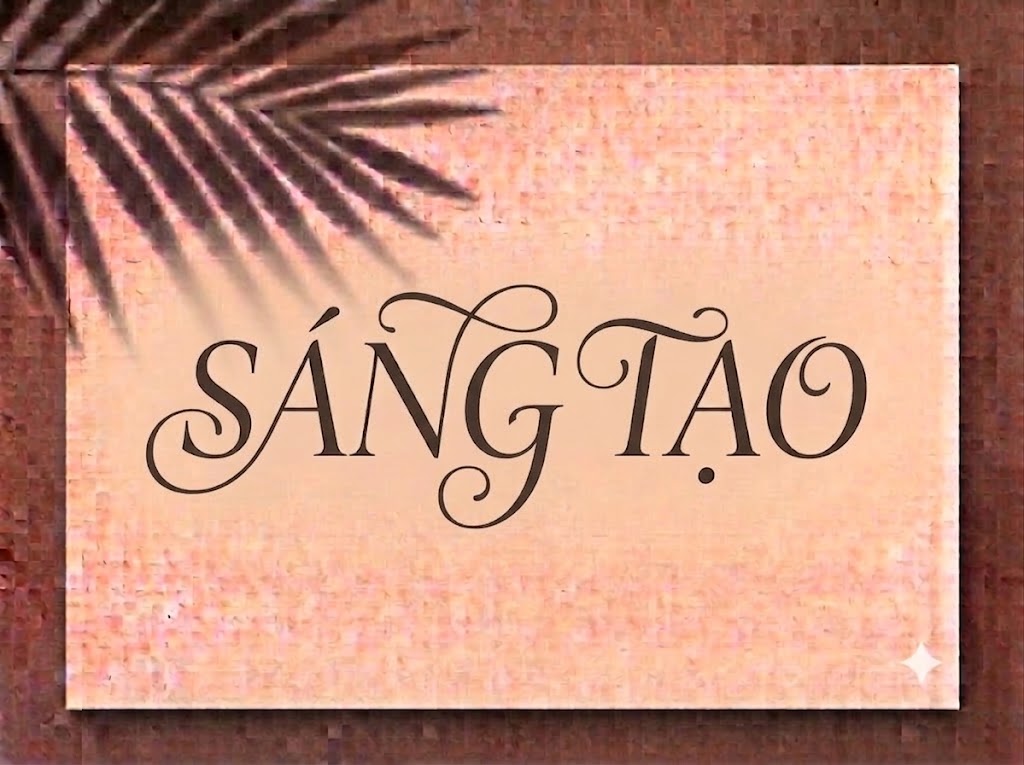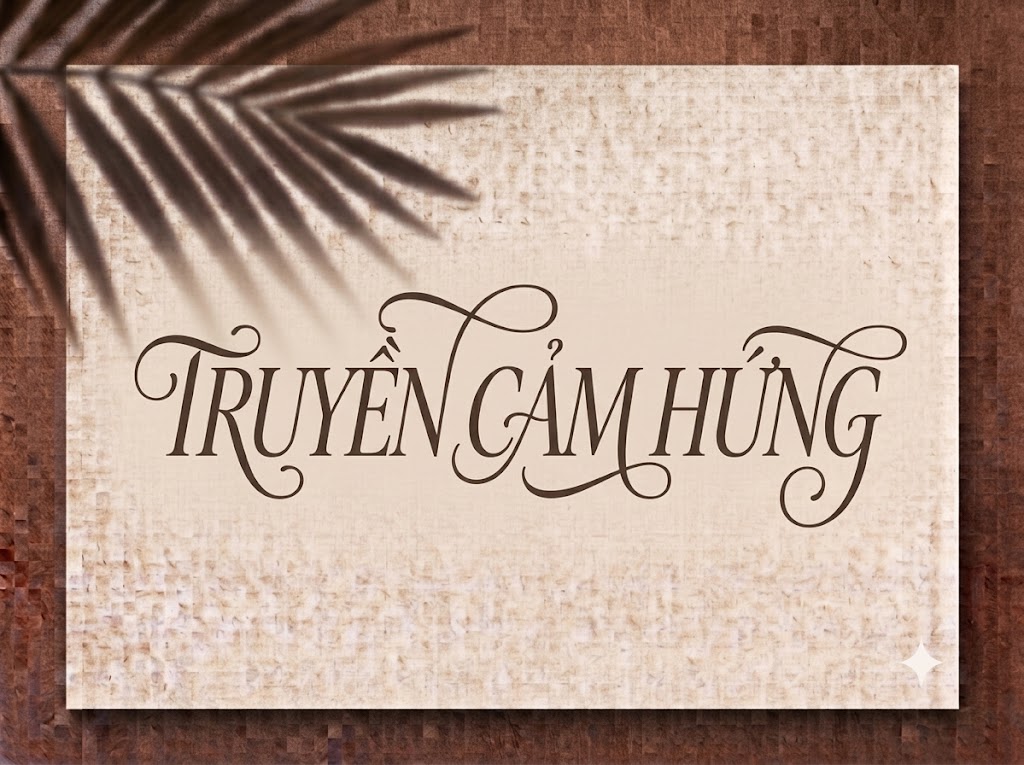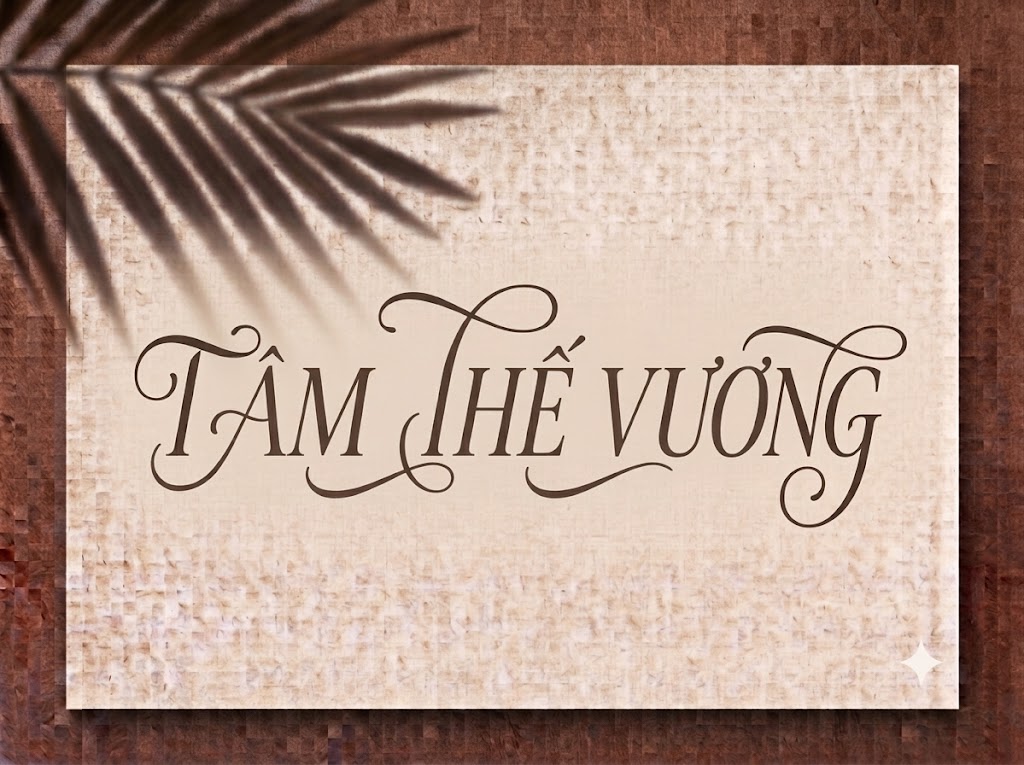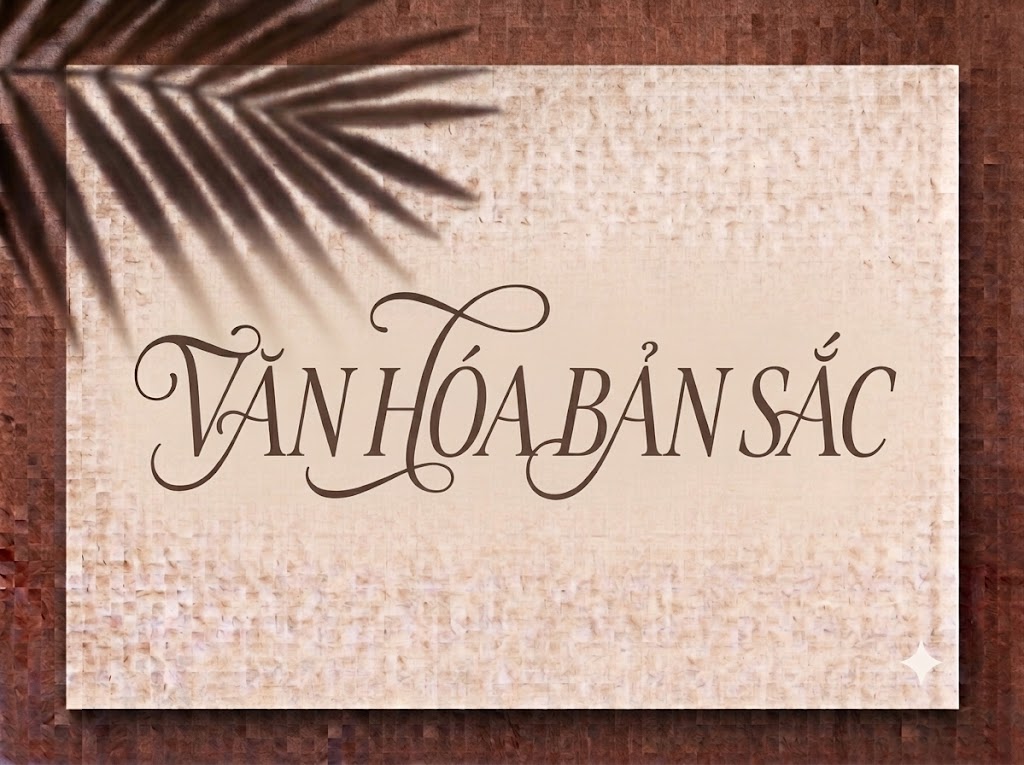
1FTV VIP Belove Melody
Trong thiết kế đồ họa cao cấp, nhận diện thương hiệu hay làm truyền thông hình ảnh cho ngành thời trang, trang sức và cưới hỏi, các kiểu chữ Serif sở hữu nét uốn lượn (swash) mềm mại luôn có sức hút đặc biệt. Một tiêu đề được tạo hình đắt giá không chỉ truyền tải nội dung mà còn lập tức thổi vào ấn phẩm chất thơ, sự thanh lịch và tinh tế.
Nếu bạn đang tìm kiếm một phông chữ hiển thị mang tinh thần lãng mạn, sang trọng với những đường nét cách điệu bay bổng cho thiệp cưới, lookbook hay tiêu đề video ngắn, font 1FTV VIP Belove Melody chính là lựa chọn hoàn hảo.
Giới thiệu về font 1FTV VIP Belove Melody
Font 1FTV VIP Belove Melody là bộ chữ hiển thị có chân (serif display) kết hợp nét uốn lượn thư pháp sang trọng, mang phong cách tân cổ điển đầy tính nghệ thuật:
Tên phông chữ: 1FTV VIP Belove Melody
Được thiết kế và hoàn thiện bài bản trên phần mềm Glyphs, phông chữ đem lại khả năng hiển thị mượt mà trên mọi độ phân giải. Bạn có thể tự tin phóng lớn chữ trên các ứng dụng đồ họa chuyên nghiệp hay phần mềm dựng phim mà không lo gặp tình trạng vỡ nét hay răng cưa.
Đặc điểm nổi bật của phong cách thiết kế VIP Belove Melody
Sức hút thị giác của font 1FTV VIP Belove Melody đến từ giai điệu thanh thoát trong từng đường nét:
Nét uốn lượn swash nghệ thuật: Điểm đắt giá nhất của phông chữ nằm ở các đường nét cách điệu vươn dài đầy kiều diễm ở các chữ cái in hoa như T, B, M, R, P. Sự mềm mại này tạo nên nhịp điệu bay bổng đúng như tên gọi “Melody”.
Tỷ lệ nét thanh đậm thanh lịch: Sự chênh lệch giữa các nét dọc mềm mại và nét ngang mảnh mai đem lại chiều sâu thị giác kịch tính, gợi nhớ đến phong cách thiết kế của các thương hiệu thời trang cao cấp.
Bộ ký tự thay thế phong phú: Tích hợp các biến thể ký tự nghiêng thư pháp cá tính, giúp các designer linh hoạt sáng tạo nhiều kiểu tiêu đề độc bản.
Khoảng cách giữa các chữ (kerning) và độ giãn dòng được tính toán chuẩn xác, giúp các đường nét kéo dài khi đứng cạnh nhau không bị dính nét hay rối mắt.
Tích hợp trọn vẹn bộ chữ cái hoa, dãy chữ số 0-9 dáng đứng thanh lịch cùng hệ thống ký tự đặc biệt, dấu câu thông dụng.
Bản Việt hóa chuẩn chỉnh giúp bạn hoàn toàn yên tâm thiết kế các văn bản tiếng Việt có dấu mà không gặp lỗi nhảy font hay mất ký tự.
Hình ảnh demo thực tế của font 1FTV VIP Belove Melody
Khả năng hiển thị của phông chữ này được tối ưu rất tốt trên nhiều tỷ lệ kích thước khác nhau:
Kích thước nhỏ (12pt – 24pt): Cấu trúc chữ đứng ngay ngắn cùng khoảng hở nội tại rõ ràng giúp câu chữ và dãy số vẫn hiển thị sắc nét, ngay hàng thẳng lối trên màn hình di động.
Kích thước lớn (36pt – 72pt): Đây là đất diễn lý tưởng nhất để 1FTV VIP Belove Melody phô diễn toàn bộ sự kiêu sa, quyến rũ của các đường nét uốn lượn ở đầu chữ T, B, M, tạo tác động thị giác mạnh mẽ cho các dòng tiêu đề chính.
Ứng dụng trong thiết kế đồ họa và làm video
Sở hữu nét cá tính lãng mạn và đầy tính nghệ thuật, font 1FTV VIP Belove Melody mở ra không gian ứng dụng vô cùng rộng lớn:
Video ngắn (TikTok, Reels, Shorts): Phông chữ serif dáng bay bổng này hiển thị rất đẹp trên khung hình đứng tỷ lệ 9:16. Nó cực kỳ ăn nhập với các video vlog cưới, phong cách sống, review mỹ phẩm, trang sức hay thời trang nghệ thuật.
Ảnh thu nhỏ YouTube (Thumbnail): Lựa chọn tuyệt vời cho các kênh làm nội dung về âm nhạc lofi, acoustic, chữa lành, vlog gia đình hoặc review đồ hiệu nhờ giao diện tinh tế và thu hút.
Thiết kế bìa Lookbook, Thiệp cưới và Poster: Hoàn hảo cho các sản phẩm truyền thông thuộc lĩnh vực váy cưới, sự kiện lãng mạn, spa, mỹ phẩm hoặc triển lãm nghệ thuật.
Nhận diện thương hiệu phân khúc Luxury: Thích hợp làm logo dạng chữ khối, menu nhà hàng hay khách sạn sang trọng, thiệp mời sự kiện VIP và bao bì nước hoa cao cấp.